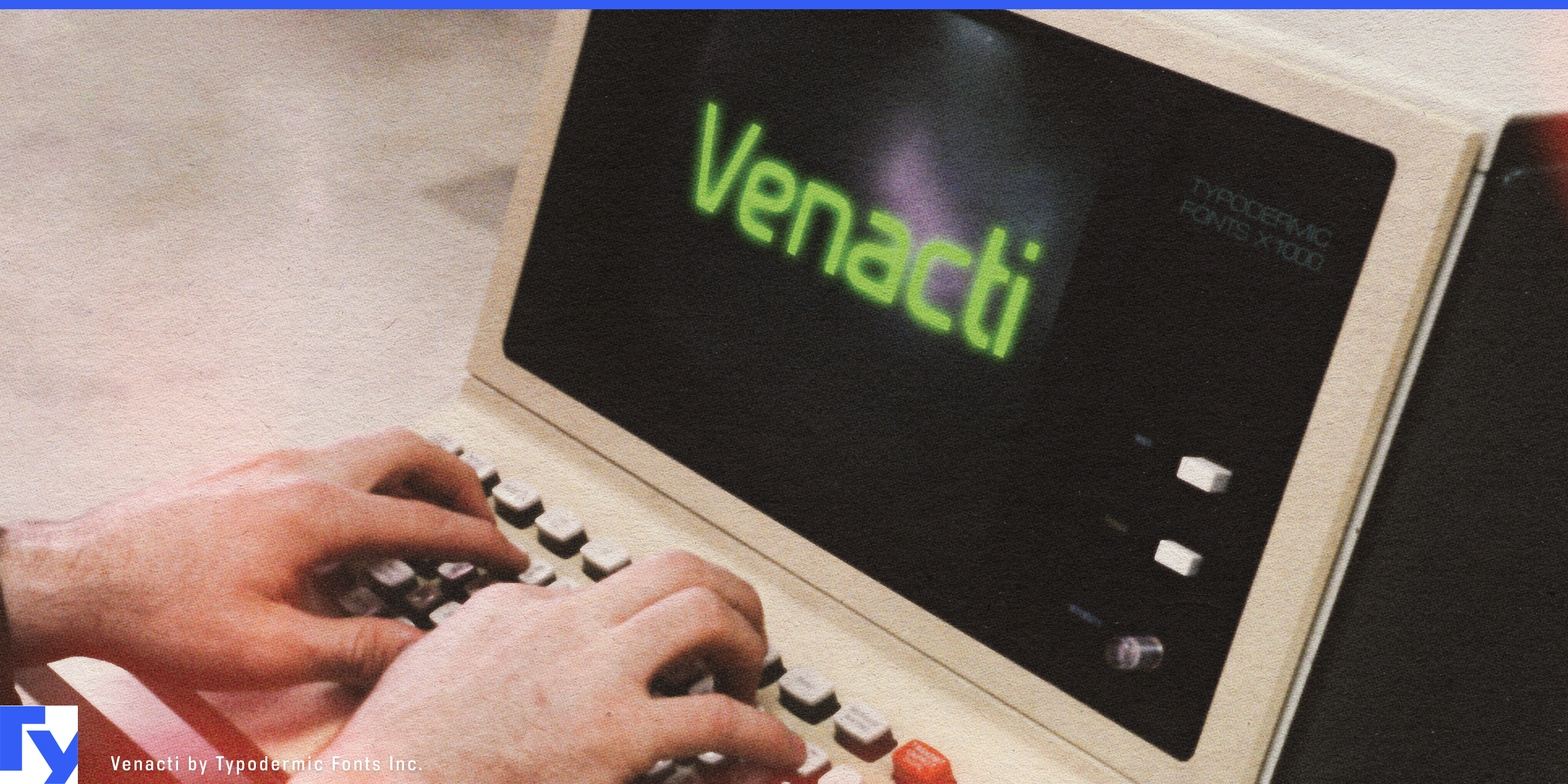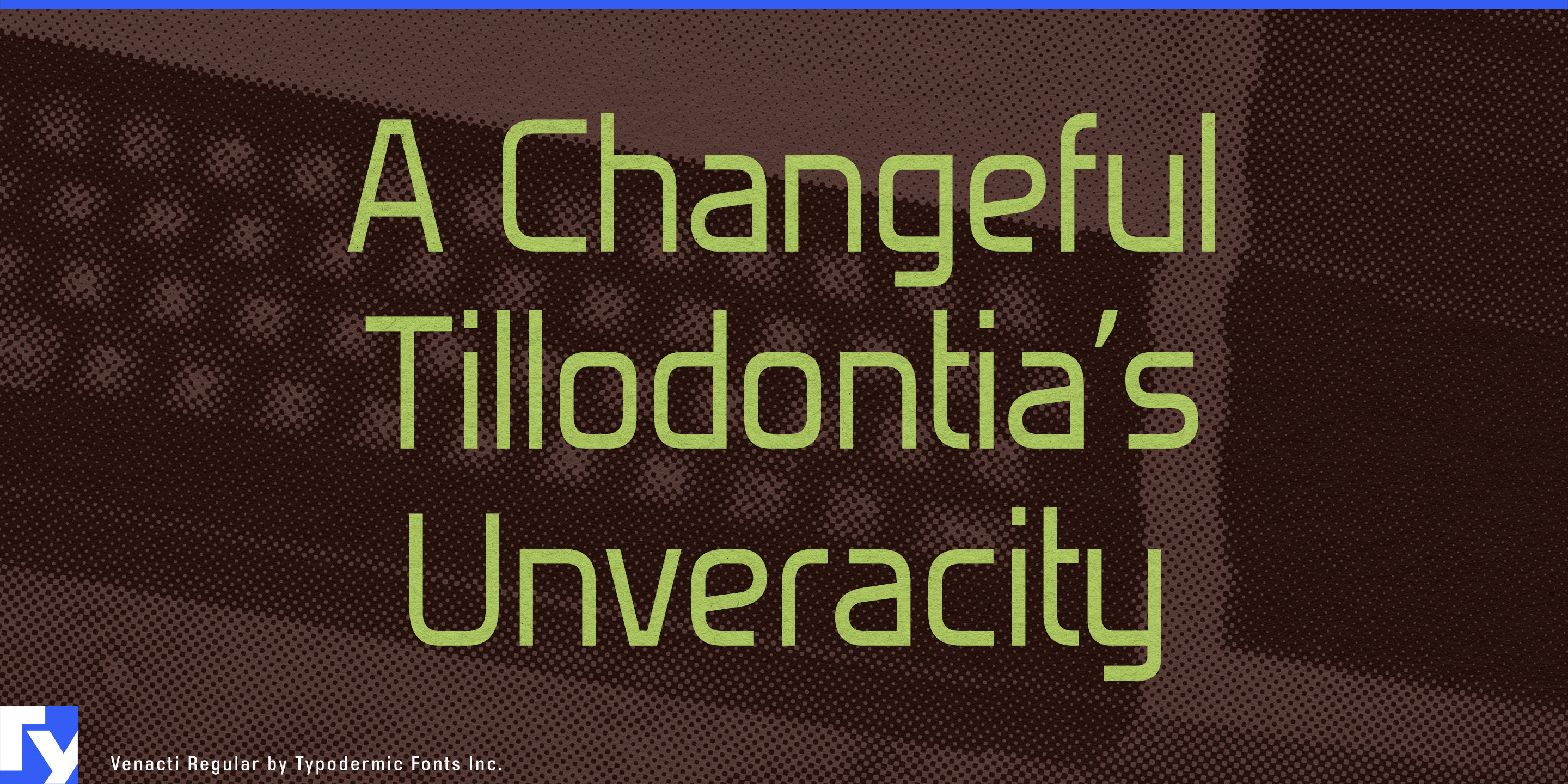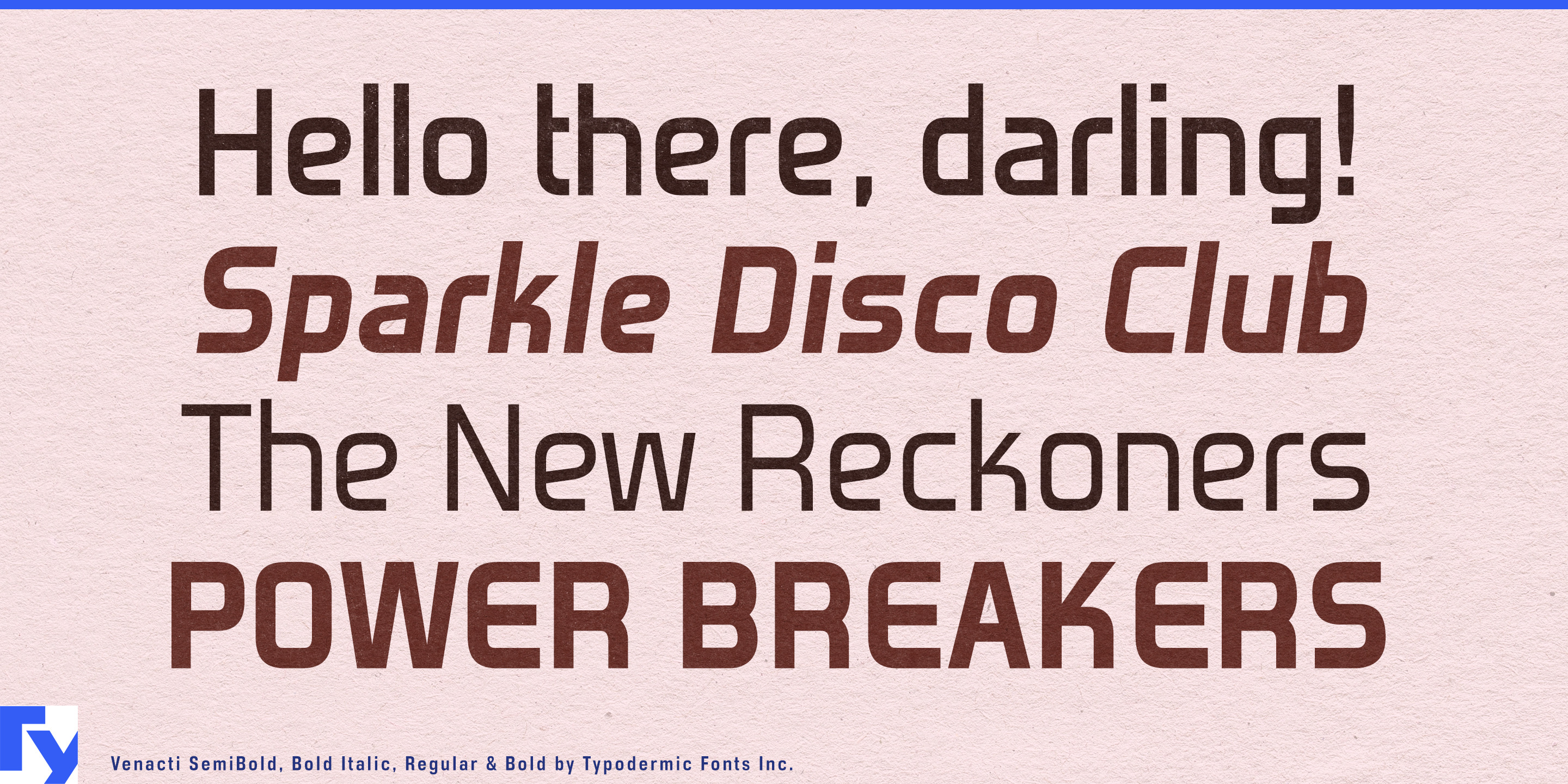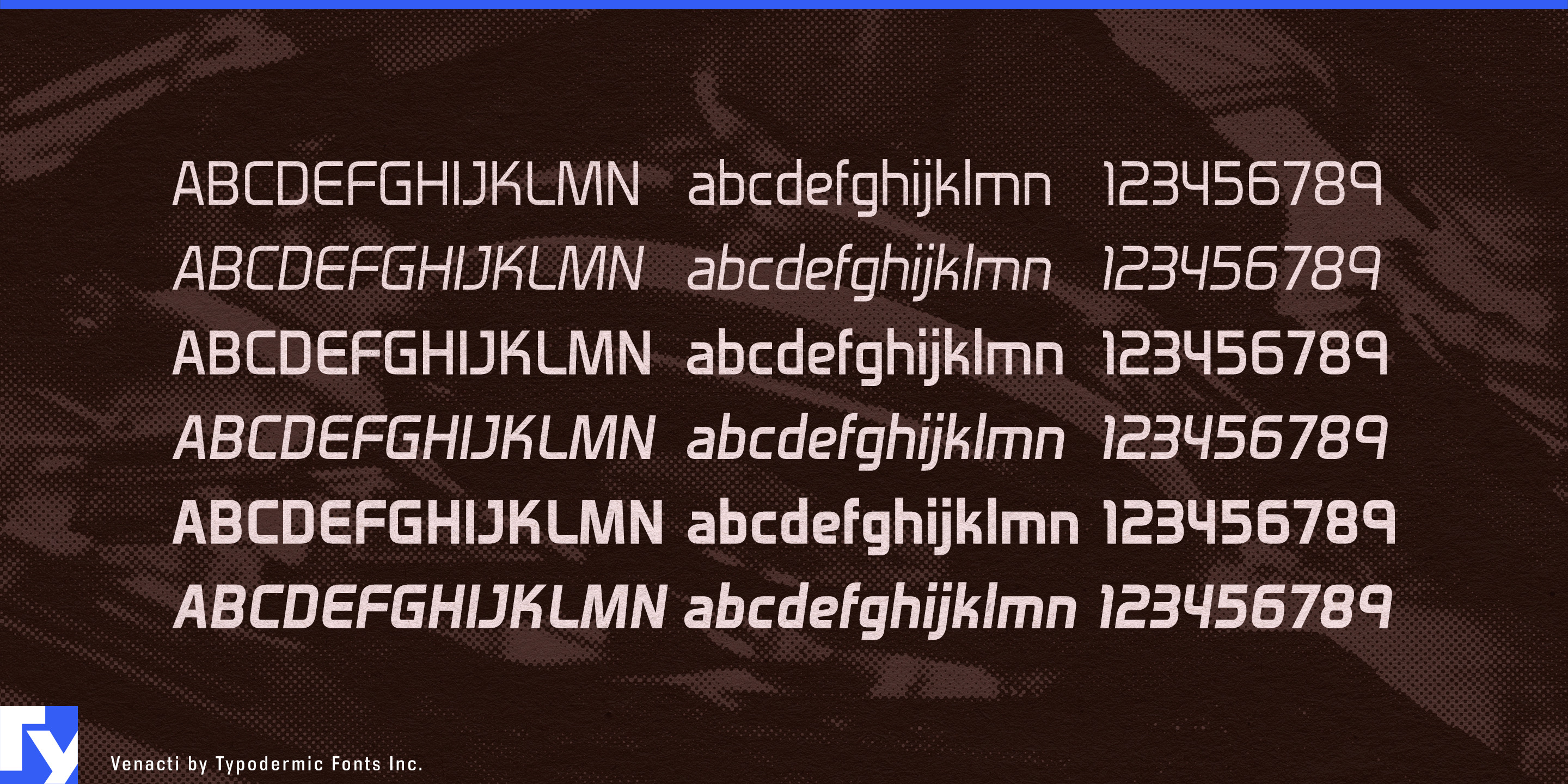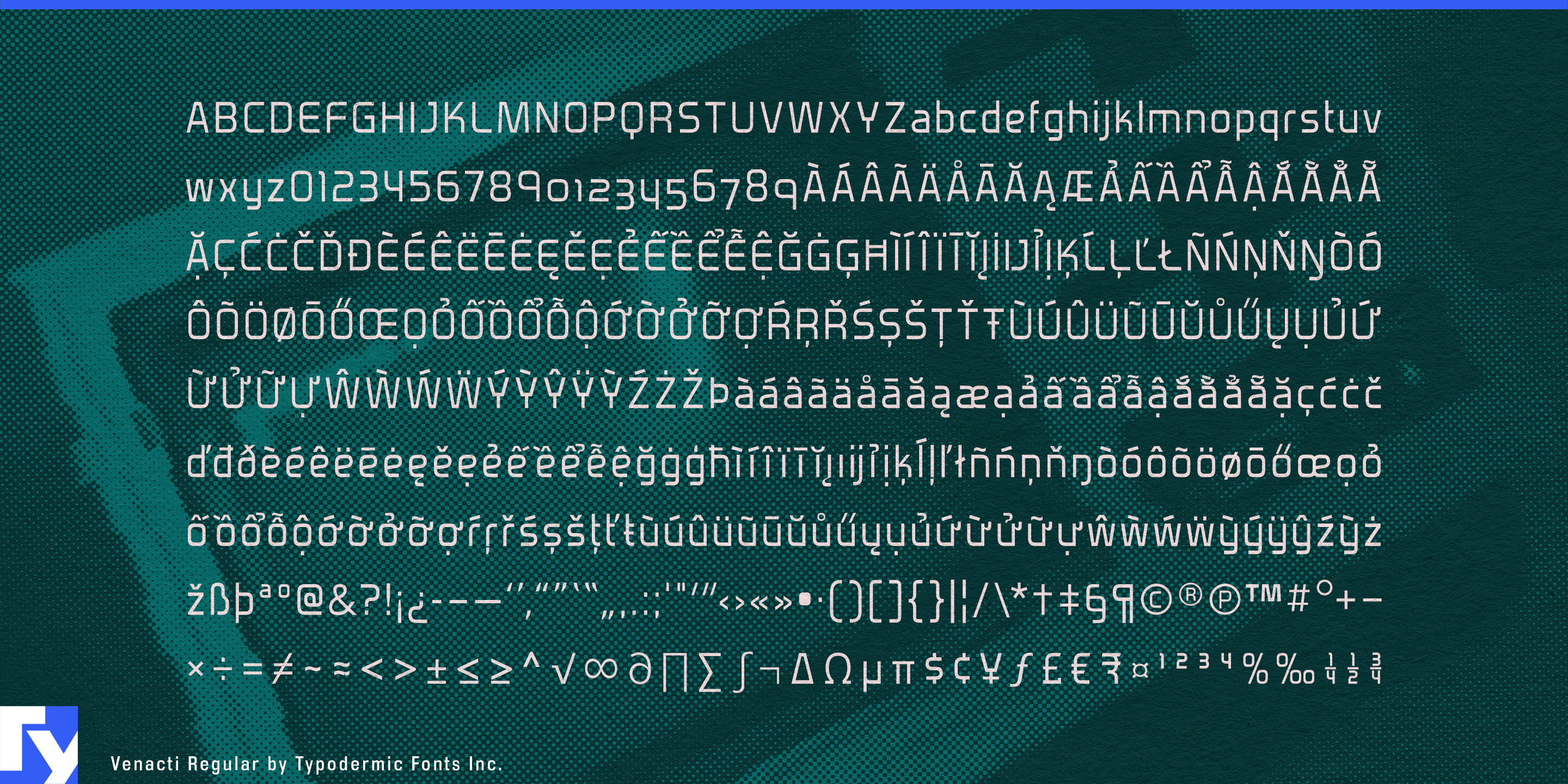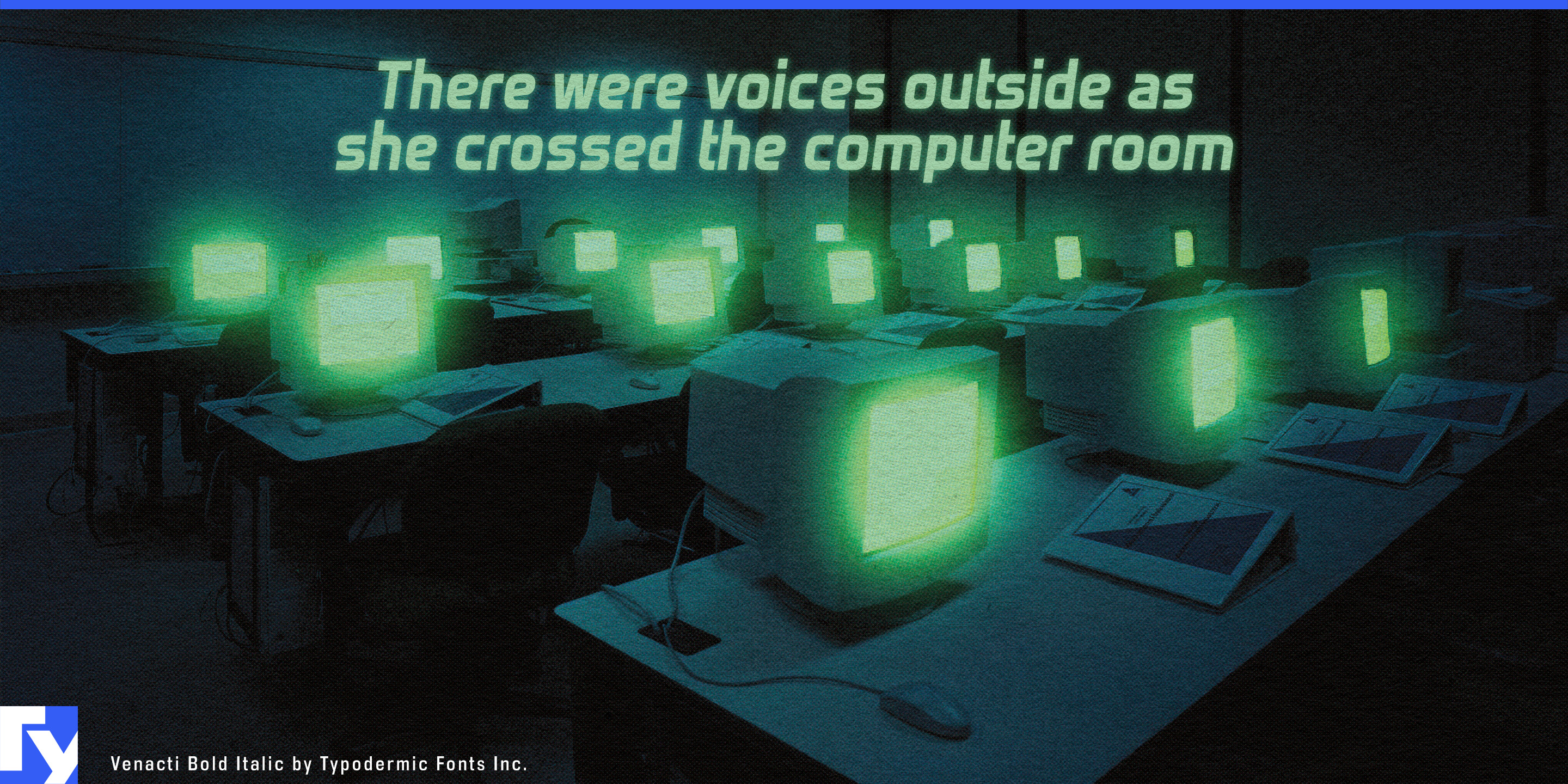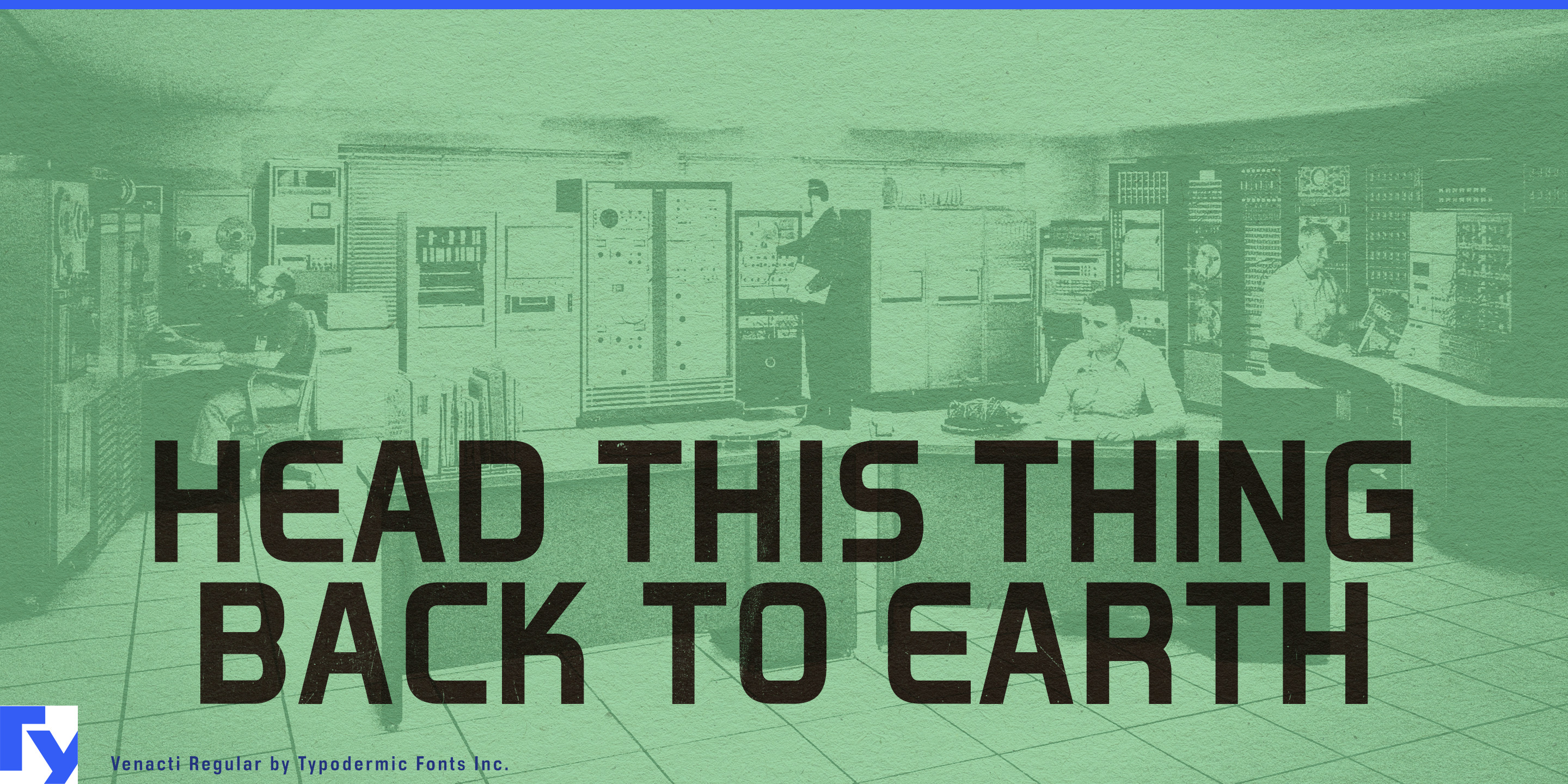
Venacti
La typographie technique impose souvent un choix entre caractère et utilité. Une police d'affichage peut donner à un kit de robotique, un panneau de commande ou une exposition scientifique une allure technologique convaincante, puis devenir malcommode dès qu'il faut composer instructions, étiquettes, références de modèles, légendes ou explications. Une sans empattement neutre résout le problème de lecture, mais peut perdre le contexte technologique. Venacti occupe l'espace utile entre ces deux extrêmes.
Créée à l'origine sur commande de la BBC, Venacti associe une géométrie rectangulaire à des détails qui évitent la rigidité. Terminaisons verticales adoucies, diagonales effilées, larges contrepoinçons, jonctions compactes et courbes subtilement superelliptiques tempèrent sa structure carrée. Elle garde une allure technique, mais son dessin ouvert et ses minuscules fonctionnelles permettent de prolonger le même langage visuel au-delà des titres.
Cet équilibre rend Venacti particulièrement utile aux activités scientifiques et technologiques pratiques : expositions de planétariums, robots programmables, kits d'apprentissage de l'électronique, fusées miniatures, expériences de classe, graphiques d'ateliers de fabrication et publications scientifiques pour enfants. Elle passe naturellement du titre aux étiquettes de schémas, légendes, consignes, mesures et courts passages explicatifs sans transformer chaque information en accessoire de science-fiction.
Les mêmes qualités conviennent aux synthétiseurs, interfaces audio, instruments de laboratoire, projets d'électronique à monter soi-même, matériel de robotique, équipements de test et panneaux de commande. Venacti donne aux libellés de fonctions, réglages, caractéristiques et numéros de modèles un contexte technique ; ses chiffres distinctifs sont particulièrement utiles lorsque mesures, scores, références de pièces et désignations d'appareils occupent une grande place visuelle.
Venacti peut aussi suggérer l'informatique rétro et la science-fiction institutionnelle sans recourir aux pixels, à la chasse fixe, aux formes OCR ou au lettrage littéral des terminaux. Expositions sur l'histoire de l'informatique, graphiques de matériel restauré, laboratoires fictifs, stations de recherche, systèmes de vaisseaux spatiaux et jeux axés sur la technologie peuvent l'employer pour évoquer les machines et le calcul tout en accueillant une langue ordinaire. Trois graisses accompagnées de leurs italiques étendent ce vocabulaire aux titres, étiquettes, caractéristiques, textes courts et informations mises en évidence.